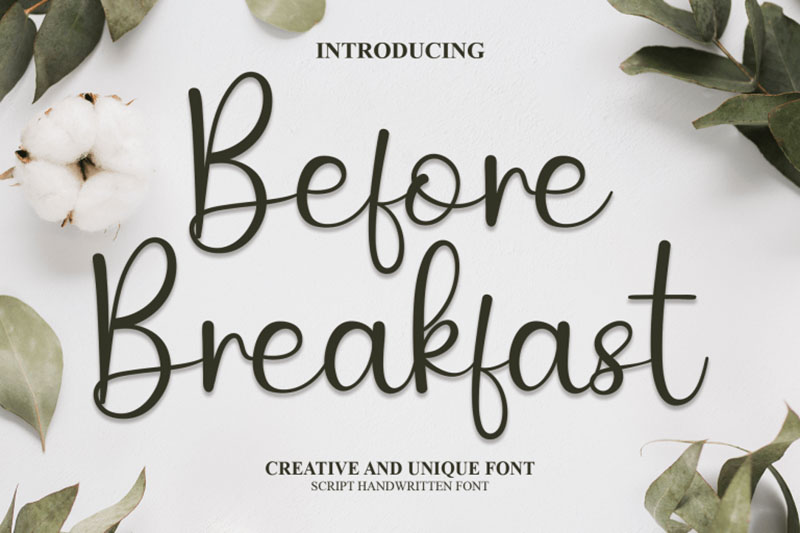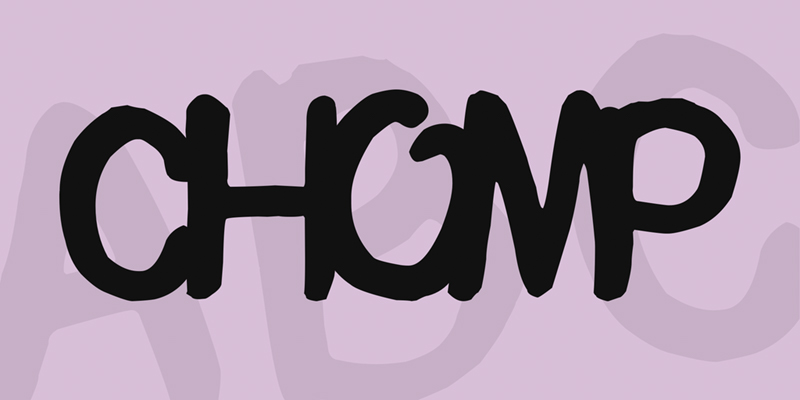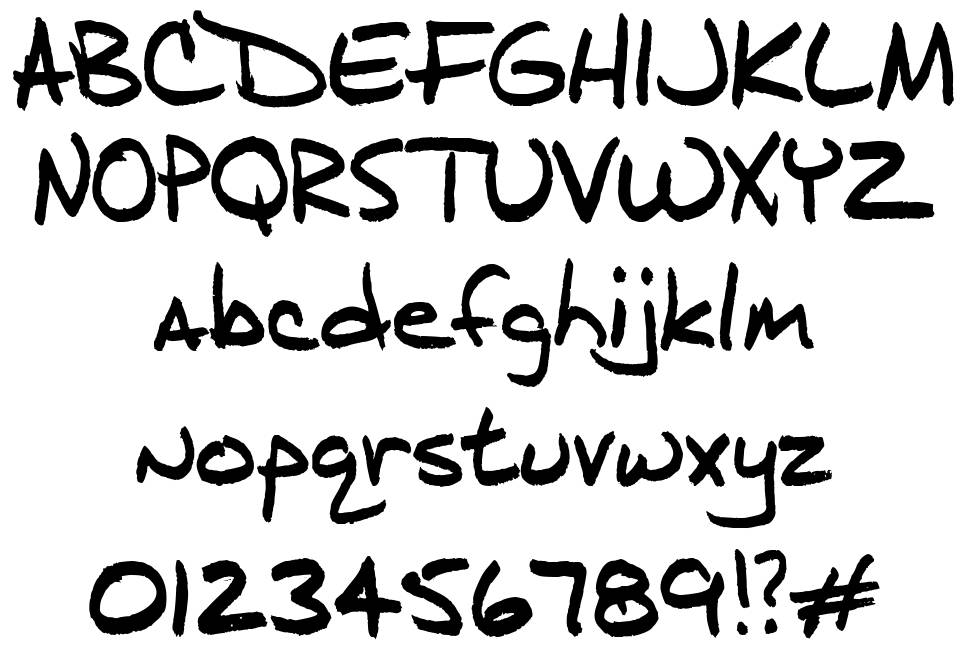
Font chữ viết tay Việt đang được khá nhiều người dùng là designer tìm kiếm và quan tâm trong thời gian gần đây. Hãy cùng tham khảo thêm font viết tay Việt hoá qua bài viết này.
Font viết tay Việt hóa là gì?
Phông chữ Viết tay (Font Handwriting) là dạng phông chữ sống động, mang đậm tính cá nhân, thường được sử dụng cho các thiết kế đồ họa chuyên nghiệp, thư mời, banner, ảnh,… giúp thiết kế trở nên tự nhiên và thân thiện hơn.
Tính năng nổi bật của bộ font chữ viết tay
Những font chữ viết tay mang lại sự đa dạng và đẹp mắt, phù hợp nhất cho các thiết kế đồ họa Photoshop, quảng cáo thời đại 4.0. Ngoài ra cũng có thể linh hoạt áp dụng trong nhiều ấn phẩm và nhu cầu sử dụng phổ thông khác.
Tổng hợp Font chữ viết tay Việt hóa đẹp
Font chữ viết tay Việt hóa ngày càng được ưa chuộng nhờ nét chữ mềm mại, tự nhiên và giàu cảm xúc. Những font này thường được sử dụng trong thiết kế poster, banner, thiệp mời hay các ấn phẩm mang phong cách sáng tạo.
Font viết tay Việt hoá Zuey Handwriting
Phông chữ viết tay này được tạo ra bởi nhà thiết kế người Úc Kirsty Hatswell bao gồm chữ thường, chữ viền, chữ in hoa, số, ký tự đặc biệt,…
Noelan Script font
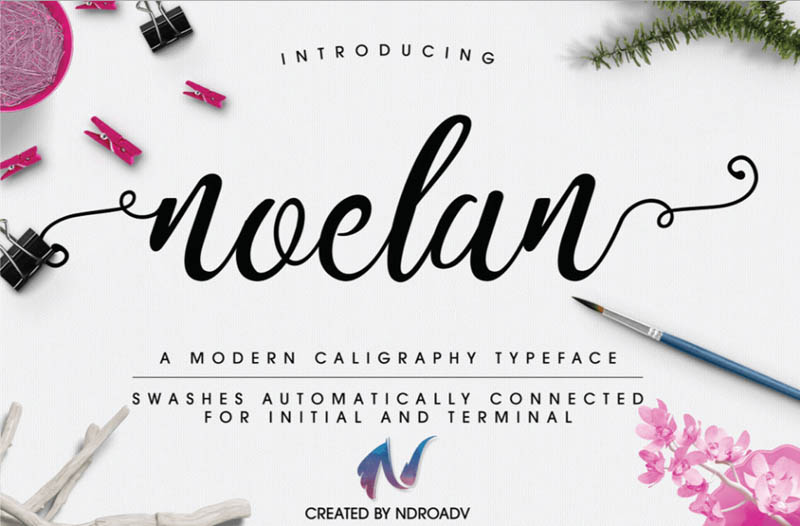
Phông chữ thư pháp phong cách hiện đại của nhà thiết kế người Indonesia Ndro Adv. Noelan có thiết kế hiện đại, gọn gàng với các ký tự viết hoa, viết thường, số, dấu chấm câu,…
Font viết tay Việt hoá Hallelujah
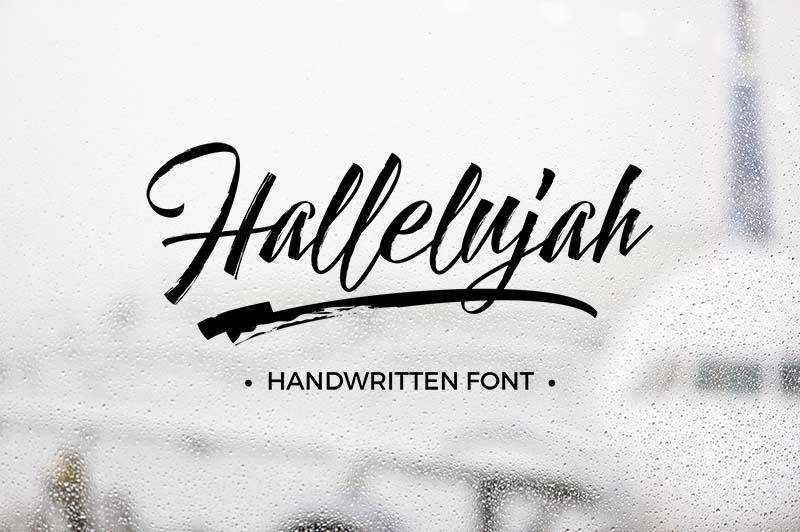
Hallelujah được thiết kế đa dạng bao gồm kiểu brush (cọ), light (vệt sáng), swashes… Bạn có thể sử dụng font này trong các dự án cá nhân như thiết kế logo, poster, áo phông, danh thiếp,…
Handycheera font
Handycheera, được thiết kế bởi Pixifield Studio ở Makassar, Indo bao gồm các ký tự viết hoa và viết thường, phù hợp để cá nhân hóa các thiết kế như logo, poster, banner,… một cách tinh tế.
Mightype font
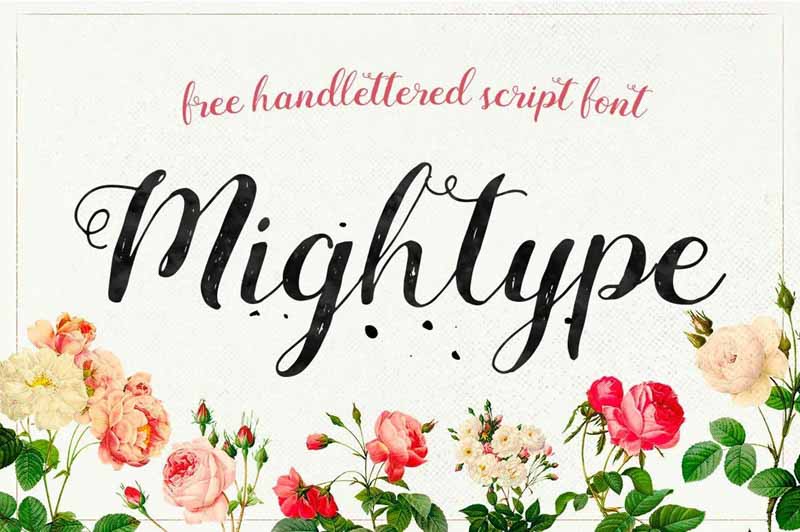
Được tạo ra bởi AF Studio, Mightype có những đường nét tinh tế, mềm mại thích hợp với các sản phẩm đồ họa trong thời trang, âm nhạc và phim.
Font viết tay Việt hoá Nothern Lights
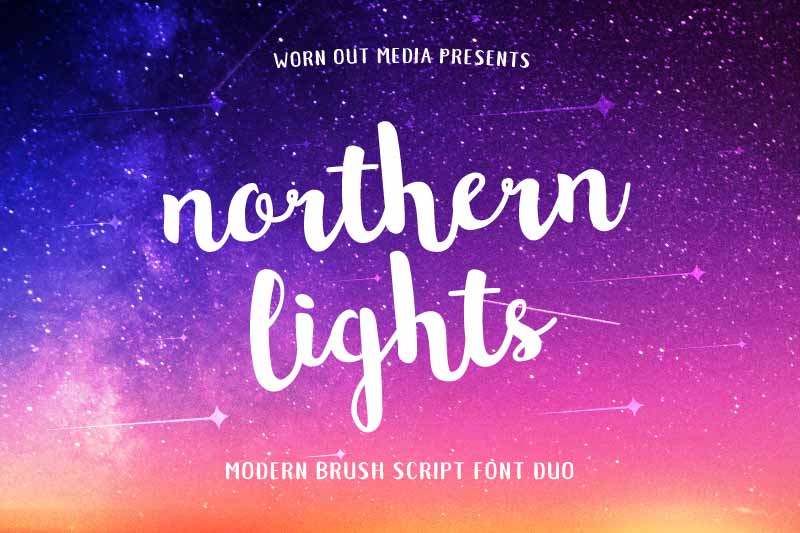
Một kiểu chữ đặc trưng của nhà thiết kế người Hà Lan Mats-Peter Forss với ảnh hưởng mạnh mẽ của chủ nghĩa tối giản Scandinavia. Northern Lights hỗ trợ đa ngôn ngữ, thích hợp để thiết kế thiệp mời đám cưới, áp phích quảng cáo, mạng xã hội,…
Wildera font
Wildera là sản phẩm của nhà thiết kế kiêm họa sĩ Lauren Lee người New York. Mẫu chữ được sáng tạo dựa trên kế hoạch thư pháp của nhà thiết kế, nhằm hướng tới các phong cách mang hơi hướng ngọt ngào hoặc châm biếm.
Selima
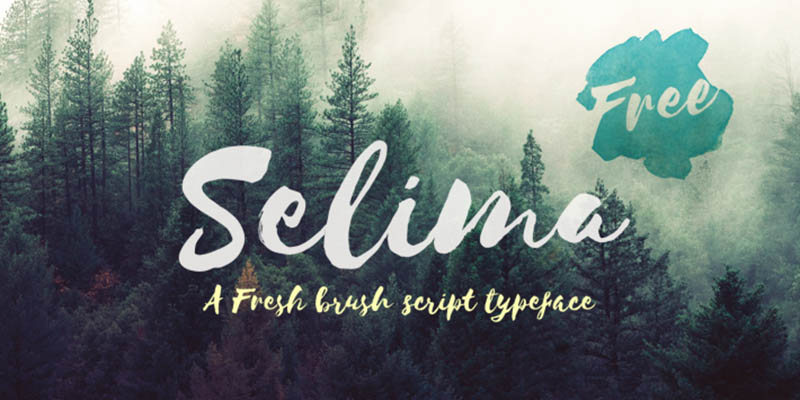
Được thiết kế bởi Jroh Creative, một công ty thiết kế sáng tạo tại Indonesia. Selima có những đường nét đặc biệt và cách sắp xếp ký tự không quá thẳng hàng, mang lại sự quý phái cho phông chữ, nhưng vẫn dễ đọc cho người dùng.
Font viết tay Việt hoá Yunus
Font Yunus được tạo ra bởi nhà thiết kế đồ họa Faraz Ahmad. Phông chữ này bao gồm nhiều thành phần, phù hợp với tất cả các bản thiết kế sáng tạo.
Cavorting
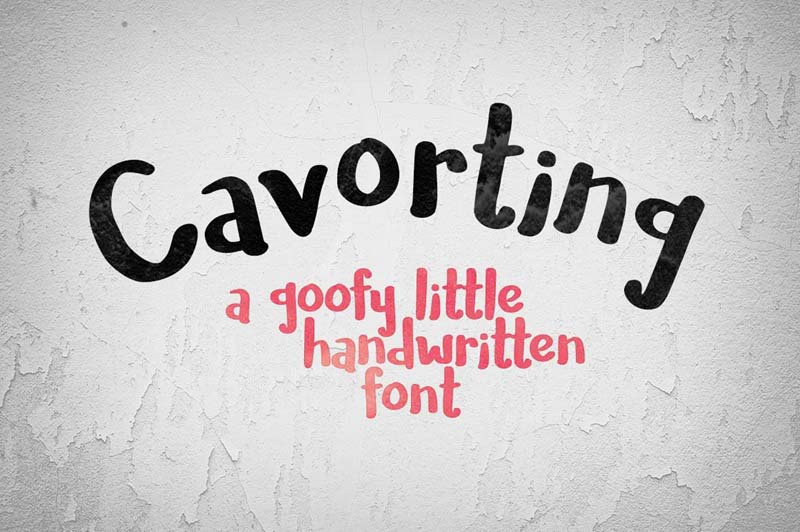
Được tạo ra bởi Missy Meyer, phông chữ viết tay Cavorting này có thể dùng cho cả mục đích cá nhân và dịch vụ thương mại.
Reis Font
Reis là thiết kế do Marcelo Reis Melo tạo ra. Phông chữ phù hợp cho poster, logo,… và có thể được sử dụng trong các mục đích cá nhân và thương mại.
Bellaboo Font
Bellaboo của Marcelo Reis Melo mang phong cách thiết kế táo bạo phù hợp tạo ra các tiêu đề, áp phích đẹp mắt.
Font viết tay Việt hoá Fofer
Fofer được tạo ra bởi Angie Raess, người sáng lập và giám đốc sáng tạo của Mousse Creative. Nói cách khác, đây là một phông chữ khá đặc biệt.
California Sans Font
California Sans là một phông chữ viết tay được tạo ra bởi nhà thiết kế người Mexico Noe Araujo. Thiết kế miễn phó bao gồm đầy đủ các chữ cái viết hoa, viết thường, số và nhiều ký tự đặc biệt khác.
Ruffle Beauty Font
Ruffle Beauty của Anis Iday mang đến phong cách tinh nghịch cho các thiết kế poster, có thể sử dụng miễn phí cho cả ý định cá nhân và thương mại.
The Skinny Font
Phông chữ này là thiết kế phổ biến nhất trên mạng của nghệ sĩ notfon1234. Thiết kế được cập nhật lần cuối đã làm sắc nét khoảng cách và phông chữ, đồng thời Skinny hoàn toàn miễn phí cho thương mại dịch vụ.
Gunny Rewritten
Dựa trên phông chữ Viết tay Gunny cũ, nhà thiết kế Vit Condak đã tạo lại font Gunny Viết tay miễn phí hoàn toàn mới.
Halo Handletter
Phông chữ viết tay thanh lịch này được phát triển bởi nhà thiết kế đồ họa Mario Arturo, người chuyên về các kiểu chữ bay bướm. Phông chữ chỉ miễn phí cho mục đích sử dụng phi thương mại.
Font viết tay Việt hoá Yore
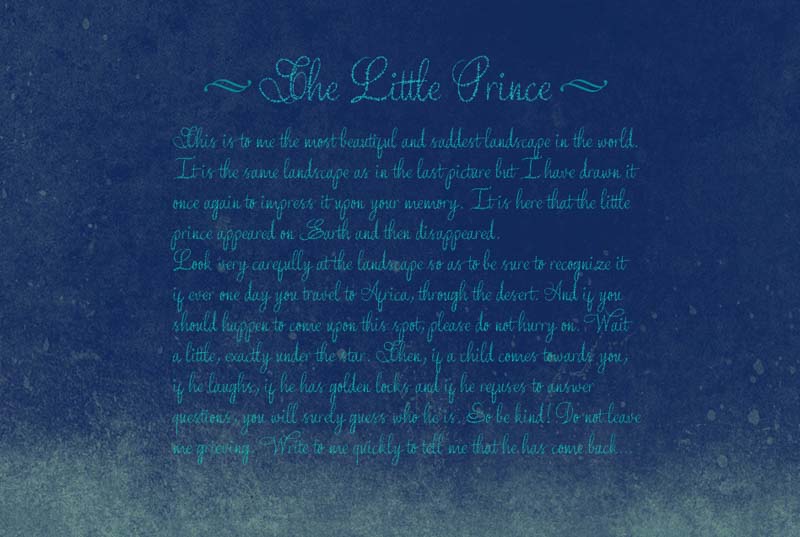
Được tạo ra bởi nhà thiết kế Việt Nam Poem Haiku, Yore mang đến nhiều thú vị hơn cho các dự án thử nghiệm nội dung và xây dựng thương hiệu so với các phông chữ truyền thống.
Whatever It Takes
Phông chữ này quay về thời kiểu chữ phấn viết bảng. Đây là một phông chữ miễn phí khi được sử dụng cho mục đích cá nhân và phi lợi nhuận. Tuy nhiên, bạn phải trả $5 cho bất kỳ mục đích dịch vụ kinh doanh nào.